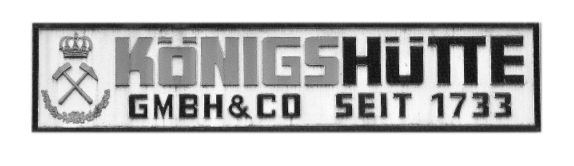
freie oder auch kaufschriften die ähnlich sind, werden wohl schwer zu finden sein weil die schrift doch einige eigenheiten aufweist. mit sicherheit ist dies keine bestehende schrift. ähnlich sind:
ggf. hier und da etwas 'eingreifen'.